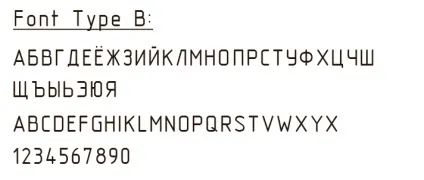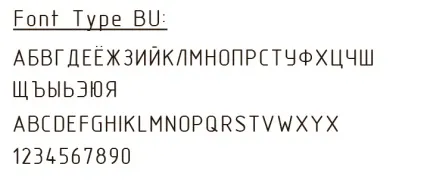
креслярські шрифти
GOST Type A
GOST Type AU
GOST Type B
GOST Type BU
Креслярський шрифт не дарма отримав назву «Гостовский». Він спроектований відповідно до вимог єдиної системи конструкторської документації, описаними в міждержавному стандарті від 1982 року. Гост 2.304-81 встановлює стандарт на креслярські шрифти, які наносяться на креслення та інші види технічної документації. Основні параметри, які регулює даний гост:
- Розмір шрифту
- Ширина букви
- Товщина лінії шрифту
- Допоміжна сітка
- Граничні відхилення ширини букв і цифр
- Висота малих і великих літер
- Відстані між символами
- Мінімальний крок рядків (інтерліньяж)
- Відстань між словами
Креслярські шрифти користуються великою популярністю серед студентів. Цифровий шрифт економить безліч часу і сил. Дозволяє зосередитися безпосередньо на проектуванні, а не на побудову нудних символів. До того ж, Гостовский шрифт дає гарантію дотримання стандартів, і зводить нанівець можливість виникнення питань з боку викладача.
Між накресленнями GOST Type A і GOST Type AU дуже невеликі відмінності. Якщо добре придивитися, стане зрозуміло що зміни стосуються таких букв як «І», «Е», «Ж», «Ю», «Х» та «М». Відмінності такі мізерні, що мало кому вдається відрізнити ці два шрифту один від одного.
Спектр застосування креслярських шрифтів виходить за рамки використання тільки в кресленні і оформленні технічної документації. Креативні дизайнери не рідко використовують подібні зображення в своїх творчих роботах. А з розвитком нових технологій, з'явилася можливість підключити подібні шрифти до сайту. Ця подія суттєво розширило потенціал створення сайтів. Шрифти використовуються в кресленні відмінно впишуться в дизайн сайту про інженерії, наукового, або будівельного характеру.